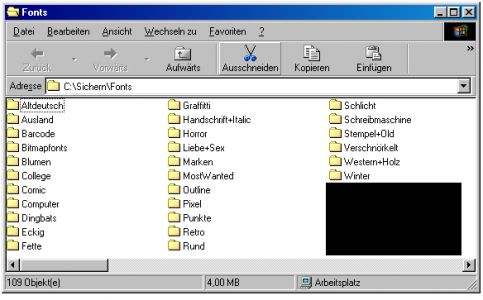
Wie sortiert man Fonts in verschiedene Ordner/Rubriken ein?
ich habe hier knapp 1.200 Fonts, welche ich gerne in mehrere Ordner aufteilen möchte.
Aktuell habe ich folgende Rubriken:
Allerdings in manchen Ordnern auch noch zuviele Fonts, es müßte nochmal unterteilt werden bzw. ein neuer Ordner her...
Meine Frage: Wie sortiert/kategoriert man sowas "professionell"?
Gibt es da irgendwelche Fachbegriffe für bestimmte Fonts?
Kenne bisher nur allgemeine Bezeichnungen wie serif, outline, ...
Ich kann Ralf nur beipflichten. Du siehst an Deiner eigenen Klassifikation, dass Fonts nach mehreren Parametern geordnet werden können: Nach Form (»Rund, Eckig«), nach Herkunft (Zeit/Ort; »Altdeutsch, Ausland«), Anmutung (»Retro, Schlicht, Winter«), Beliebtheit (»MostWanted«), etc.pp.
Ich hab mich köstlich über Deine Rubriken amüsiert – nicht, weil sie so lächerlich wären, sondern, weil sie mich stark an meine eigenen ersten Versuche der Schriftklassifikation erinnert haben. :D
Ein gutes Fontverwaltungsprogramm würde all diese Parameter auf einmal bewältigen. Schau Dir mal FontExplorer von Linotype an (ich weiß allerdings nicht, wie die Windows-Version ist/ob es eine gibt). Das Programm ist kostenlos. Du kannst eigene Gruppen erstellen, v.a. aber über Kommentare Deine Fonts taggen (manche sagen auch »verschlagworten«). Eine Schrift trägt dann z.B. die Tags ›Antiqua‹, ›statisch‹, ›Hermann Zapf‹, ›Kursive-mit-2-stöckigem-g‹, ›kommerziell-einsetzbar-weil-legal-erworben‹. :lol:
Dann kannst Du all Deine 1.200 Fonts automatisch umsortieren und Dir beispielsweise nur jene anzeigen lassen, die eine statische Anmutung haben und von Herrn Zapf gestaltet wurden.
Interessant der Hinweis auf die Arbeit von Hans-Peter Willberg, der Eintrag im Typowiki ist allerdings etwas dürftig. Kann hier jemand einen Link mit mehr Information anbieten?
Sicherlich erwähnenswert ist auch die »Matrix Beinert« von Wolfgang Beinert aus München, ein meines Erachtens hochgradig diskutabler Ansatz:
Daneben soll sich auch die ATypI mit einer modernen Klassifizierung beschäftigen, jedoch kann ich nicht sagen, wie weit die gediehen sind. Jedoch wäre es hochgradig wünschenswert, wenn sich auf internationaler Ebene eine halbwegs anerkannte Lösung etablieren würde.
Die gute alte DIN wird übrigens heute von vielen schlechter gemacht, als sie ist. Für die Schriften bis zum Fotosatz hat sie doch hervorragende Dienste geleistet und gleichzeitig immer verdeutlicht, dass ein reines Schubladendenken ohnehin nur begrenzt Aussicht auf Erfolg hat. Wenn nicht die Gruppe der »Antiqua-Varianten« im Laufe der Zeit hoffnungslos ausgeufert wäre, könnte man sie auch heute noch gut verwenden.
Lars, die Matrix Beinert ist auf jeden Fall interessant. Woran sie aber krankt, genauso wie wohl jeder klassische Schubladen-Ansatz, sei es DIN oder Willberg, ist die Tatsache, dass Schriften nach mehr als nur einer Eigenschaft klassifizierbar sind.
Nimm etwa die Courier als doofes Beispiel:
Formal wäre sie, nach Beinert, ein Kandidat für die Kategorie »2. Egyptienne [slab Serif]«. Er sortiert sie in seinem Beispiel aber unter »6. Bildschirm« ein, weil dieser Font (zufällig) zur Grundausstattung sehr vieler aktueller Betriebssysteme gehört und deswegen im Web verwendet wird. Mit dem selben Font können aber auch Drucksachen erstellt werden. Was passiert, wenn eine Firma sich die Courier als Corporate Font aussucht und ein Schriftenhaus unter gleichem Namen eine dazu passende »Courier Sans« herausbringt? Muss dann der Font die Schublade wechseln zu »4. Corporate Typography Fonts«? Oder muss ich Dubletten anlegen? Was ist, wenn ich die Courier Multilingual OpenType besitze – Umzug nach »8. Nichtrömische Schriften«? Aber das römische (bzw. lateinische) Alphabet ist doch auch mit drin!
Ich denke, die Zukunft der Schriftklassifikation liegt in einem mehrdimensionalen System, ähnlich den »tag clouds«. Da natürlich nicht jeder Desktop-Publisher seine aberhundert Fonts durchtaggen kann, wird es gemeinschaftlich erstellte und stets wachsende Tag-Sets geben, die man sich für die Fontverwaltungs-Tools der Zukunft herunterladen kann. So, wie ich Informationen über Musik-CDs bei CDDB und Konsorten abrufen und hinzufügen kann, wird das eines Tages auch für Fonts kommen. Nötig dafür wäre nur ein gut durchdachter Standard – die aktive Community ist sicherlich riesig.
Daher hatten Willberg, ich und Max Bollwage uns für eine »Stil-Einteilung«, die von der Anmutung der Schrift ausgeht, in unseren Büchern ausgesprochen und der DIN-Kommission.
Ich denke nicht, dass man so etwas gänzlich über das DIN oder die AtypI regeln kann. Aber wir können ja solche Treffen wie in Lissabon als Diskussionsort nutzen.